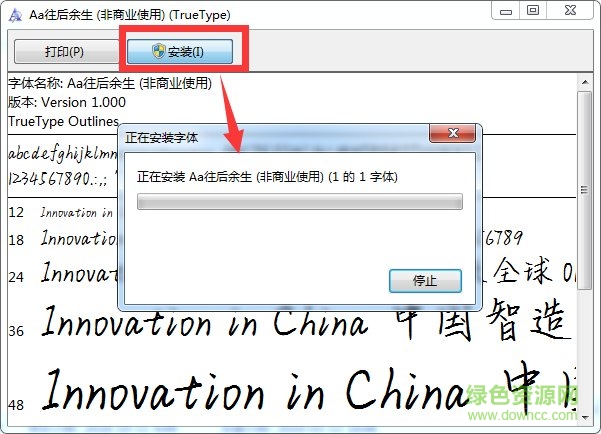
aa往后余生字體是一個(gè)很好看的字體文件。小編今天推薦的aa往后余生體支持英文、中文、數(shù)字輸入,可應(yīng)用于設(shè)計(jì)行業(yè)!喜歡aa字體的朋友千萬(wàn)不要錯(cuò)過(guò)了哦!
Aa往后余生字體外形非常大氣!這款字體沒(méi)有過(guò)多的裝飾,但是就是這樣才看上去有中說(shuō)不明白的藝術(shù)感!喜歡這款字體的朋友快來(lái)綠色資源網(wǎng)下載吧!